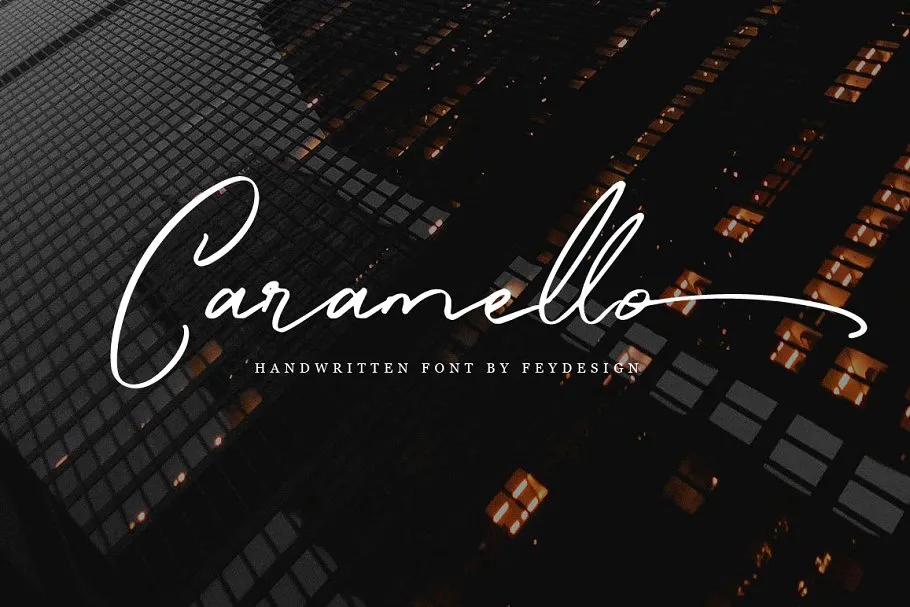
Caramello Handwritting Font – Download Grátis
Caramello Font é uma nova fonte de escrita manual com estilo script criada pelo Designer FeyType para quem busca um toque elegante e autêntico nas suas criações digitais. Essa fonte, com seu feitio de assinatura, está perfeitamente adaptada aos mais diversos usos em design: desde elementos gráficos até logomarcas, etiquetas ou até mesmo para personalizar camisetas e materiais promocionais. Seja você um designer gráfico, uma agência de marketing digital, uma empresa de comunicação visual ou até mesmo um casal querendo criar um lembrete inovador para sua cerimônia de casamento – a Caramello Font está aqui para atendê-lo. Sua elegância manual e modernidade proporcionam o ideal equilíbrio entre sofisticação e versatilidade, permitindo que você personalize suas criações com estilo e originalidade.